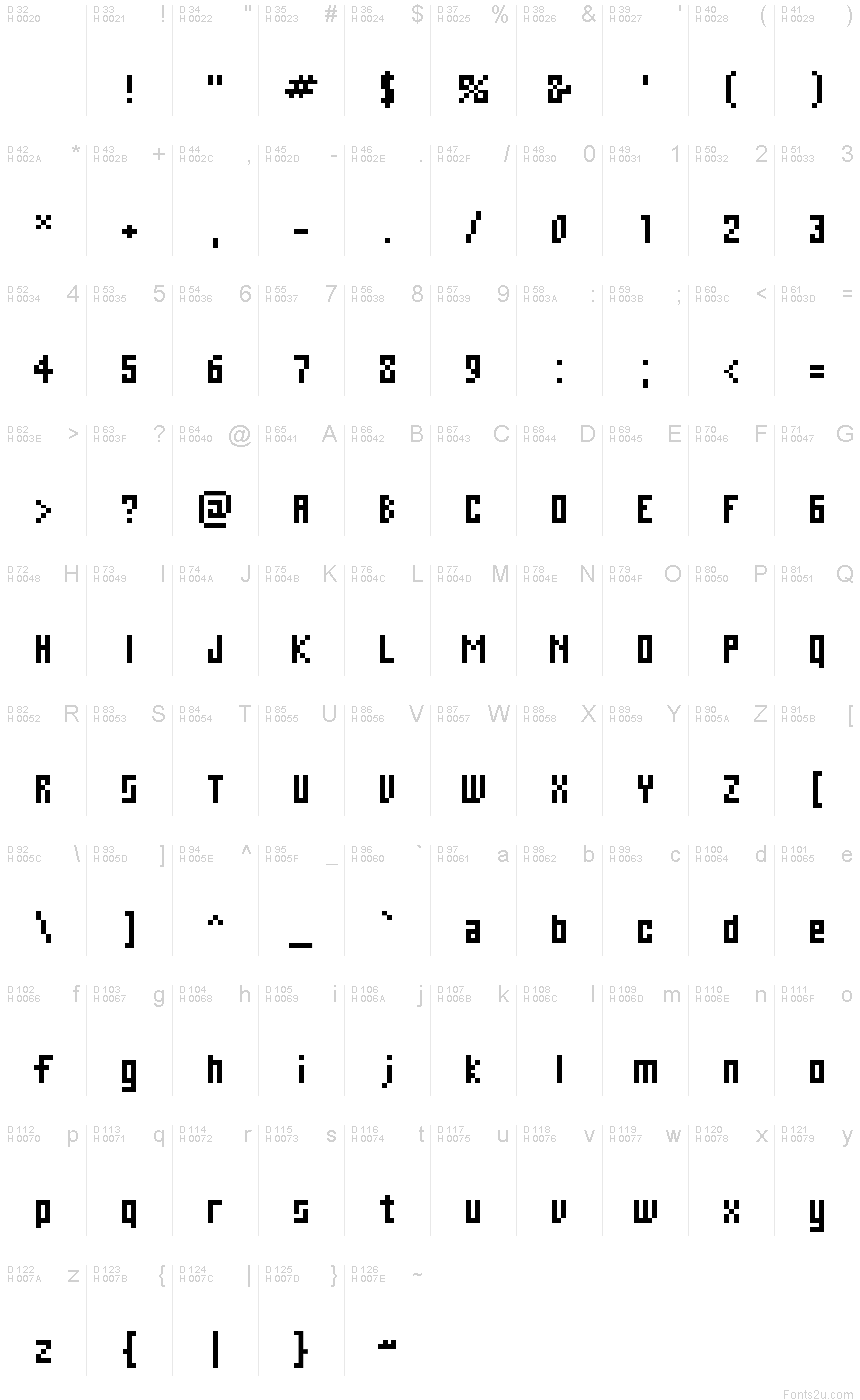
C Web Large от Andreas Carlsson (Nofont) — это бесплатный растровый пиксельный шрифт с высокими, похожими на лестницу штрихами и четкими прямыми углами, которые мгновенно создают цифровой облик. Массивные вертикальные элементы и плотный кернинг придают семейству C Web уверенный вертикальный ритм, из-за чего каждое слово словно зафиксировано в сетке. Шрифт эффектно смотрится на темном фоне, особенно если позволить символам «дышать» в крупных размерах, а вспомогательный текст оформить в более мягком, современном гротеске.
C Web Large поможет придать стиль ретро-технологий игровым интерфейсам, киберспортивному брендингу, оверлеям для стримов, научно-фантастическим плакатам, обложкам в стиле пиксель-арт, дашбордам и минималистичным веб-баннерам. Выразительные черные блоки делают заголовки максимально заметными, а последовательная структура сохраняет читаемость даже коротких надписей и кнопок при низком разрешении. Этот бесплатный шрифт лучше всего использовать для ключевых фраз или элементов UI, оставляя более простые гарнитуры для основного текста.